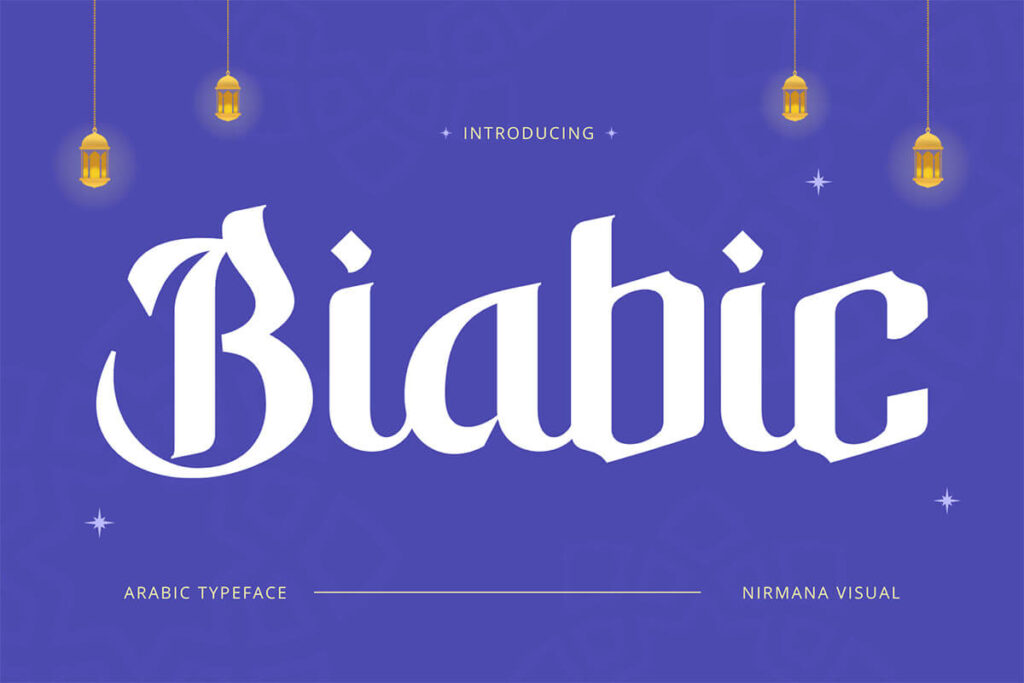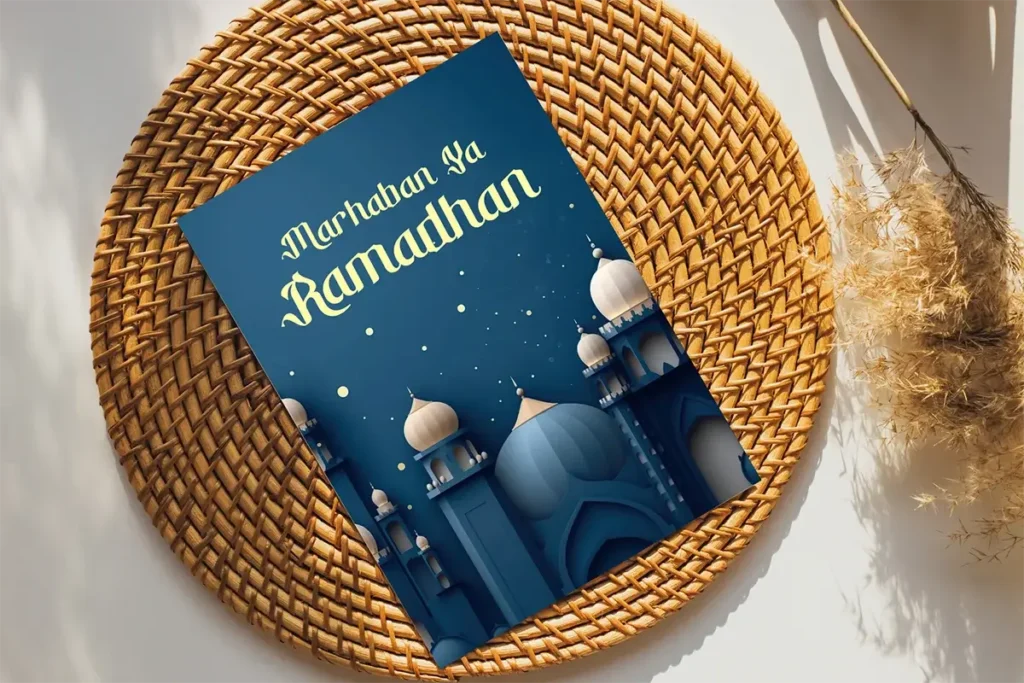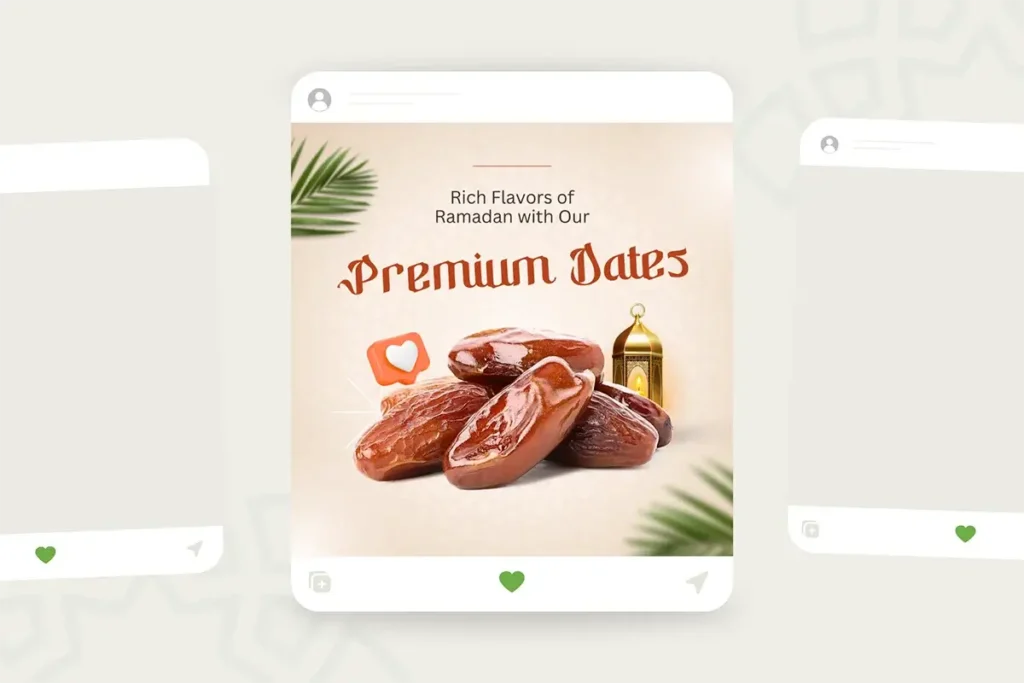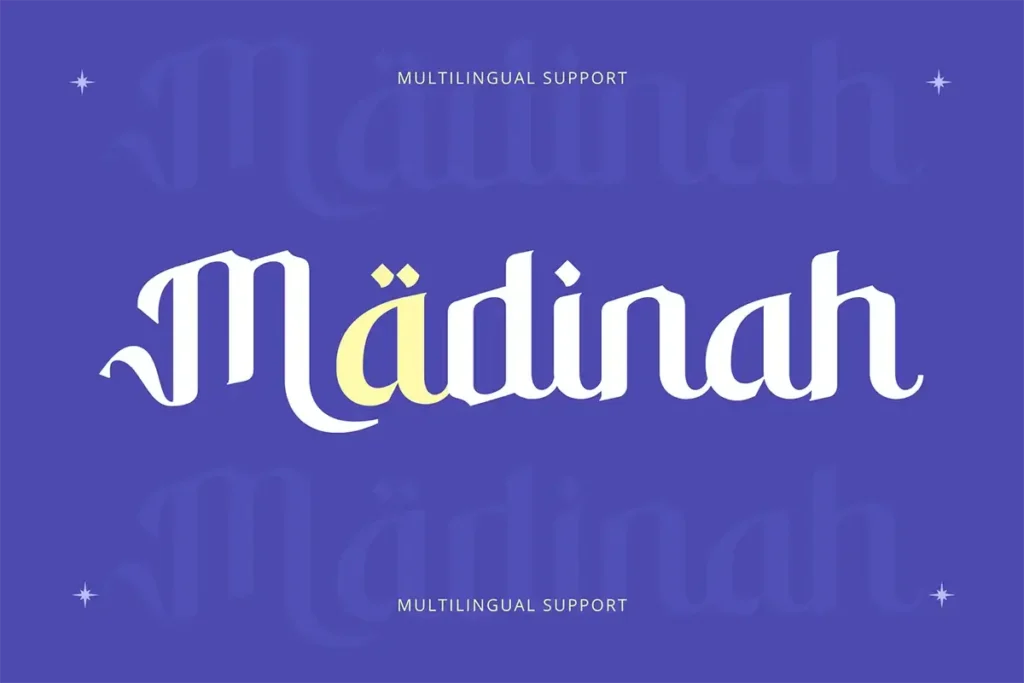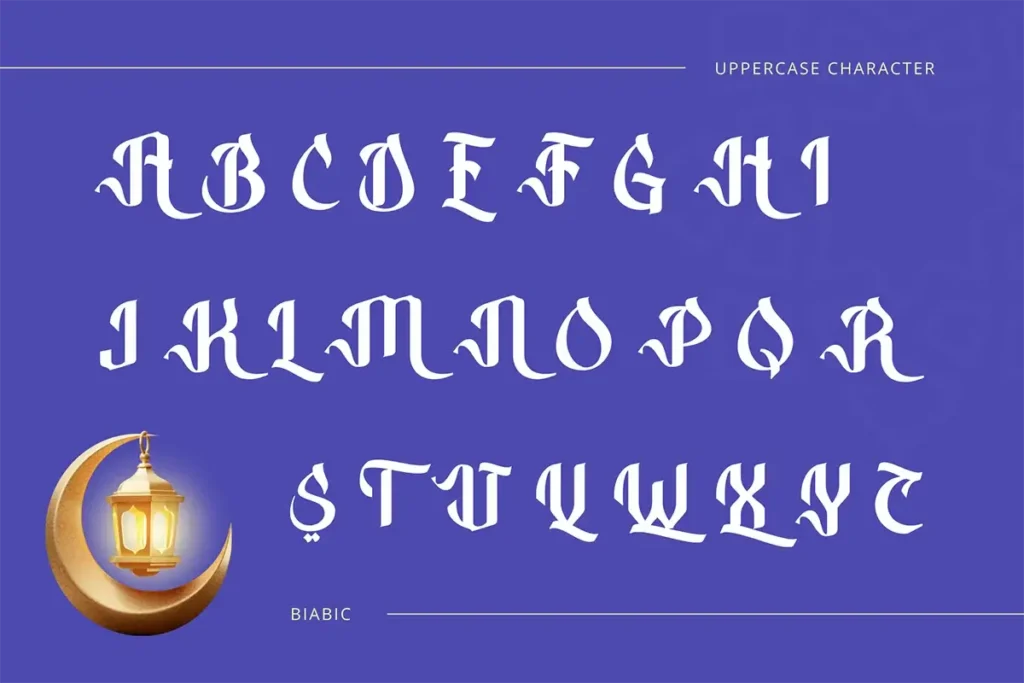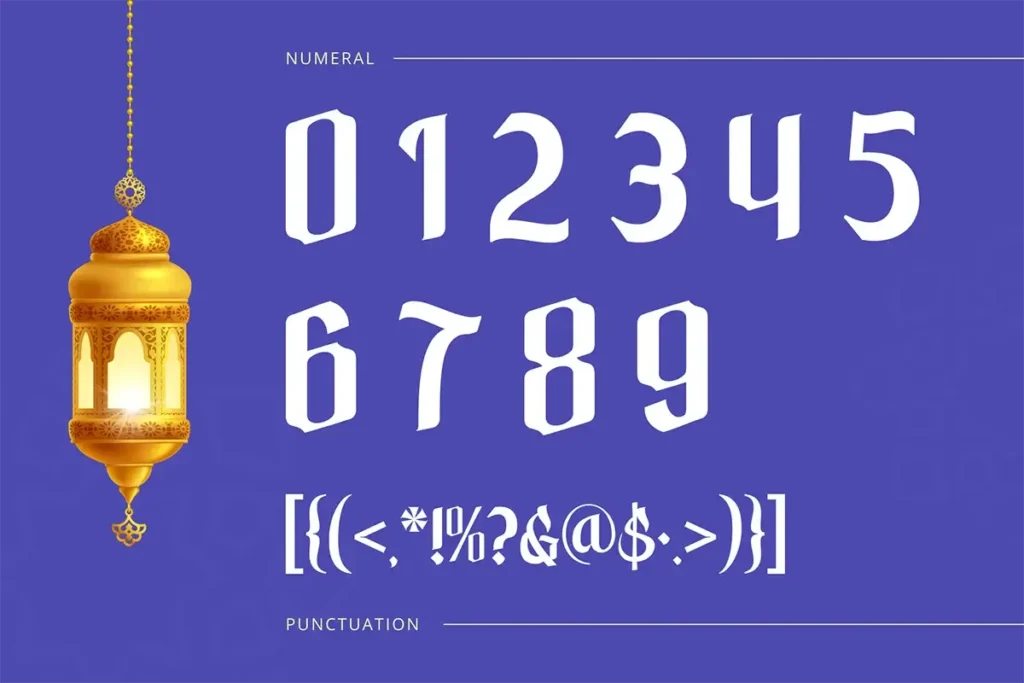
Biabic Arabic – Árabe Typeface Fonte Grátis
Inspirada na beleza da caligrafia árabe tradicional, a Biabic Arabic transmite um clima sereno, artístico e espiritual. Ideal para composições que buscam refletir temas islâmicos, como o Ramadã, essa fonte oferece uma presença visual marcante e culturalmente sensível.
Ela se adapta bem a logotipos, identidade visual, materiais editoriais, posts em redes sociais, embalagens e campanhas publicitárias. Com traços elegantes e tipografia harmoniosa, eleva projetos que exigem sofisticação e significado cultural.
Fonte Biabic Arabic com estilo islâmico, perfeita para logotipos, Ramadã, design editorial e branding com inspiração tradicional.